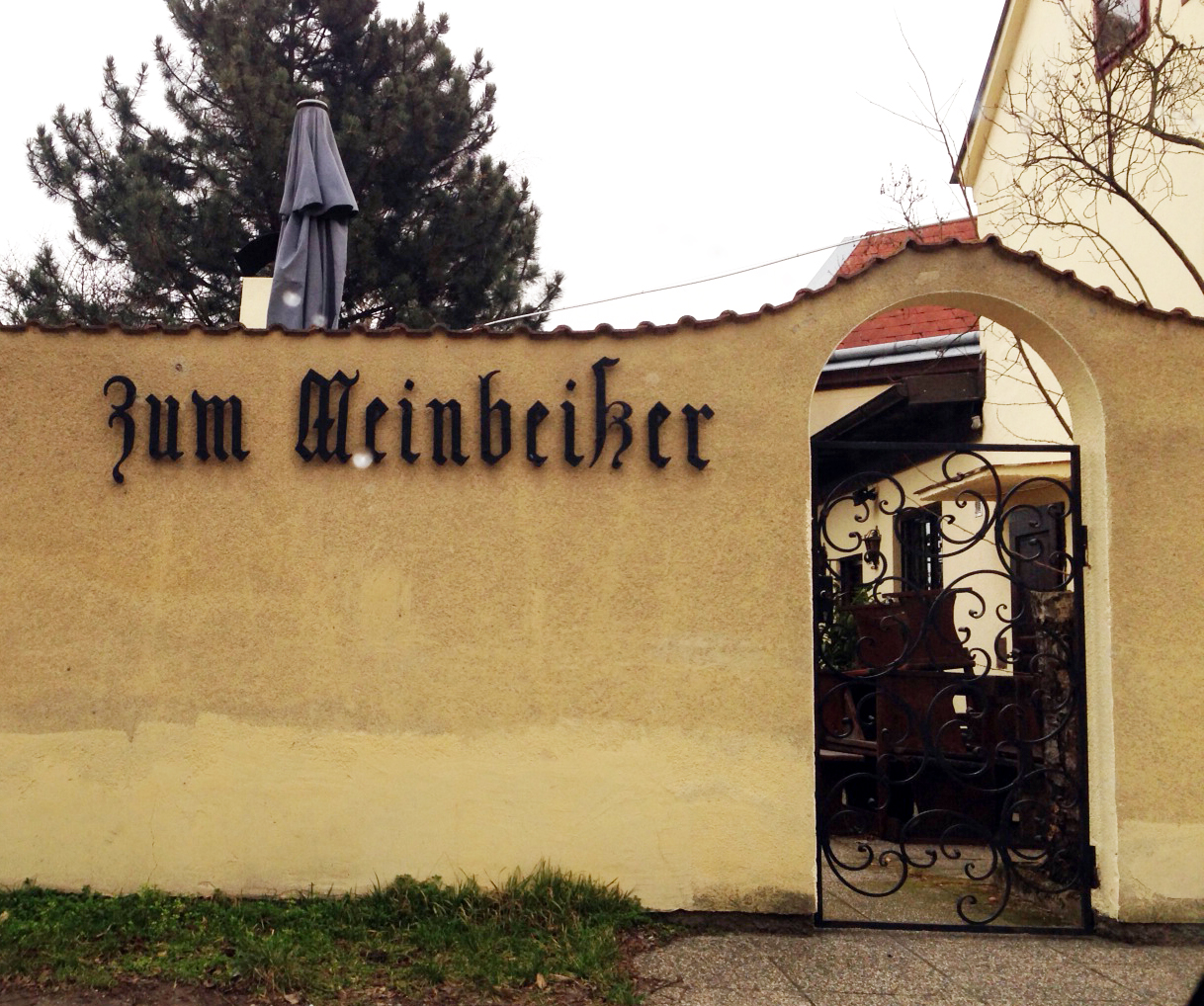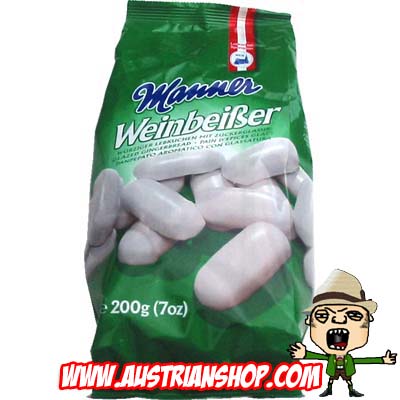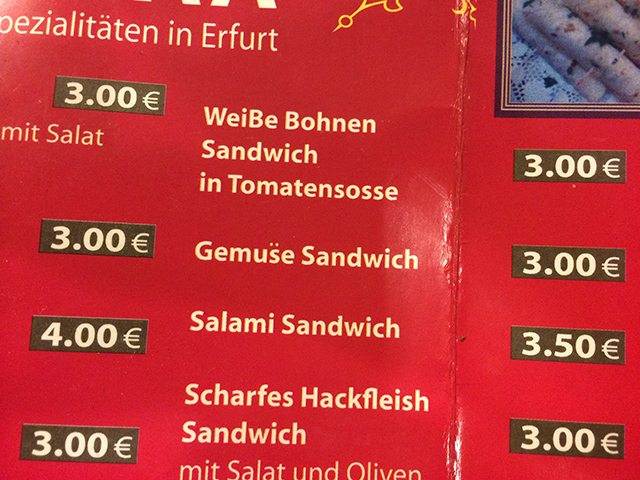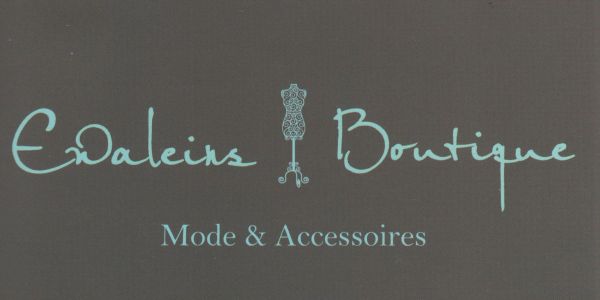
So sind sie nun mal, die Leute, die vorgeben deutsch zu sprechen, und dann Obers, Topfen, Ribiseln, Marillen und eben Weinbeißer haben
Und da ist der Weinbeißer eben dreierlei:
1. Ein mit weißem Zucherguss überberzogener Lebkuchen in Form einer Biskotte (noch so'n Ösi-Wort für Löffelbisquit)
2. Ein anspruchsvoller, den Wein bewusst genießender Weintrinker und -kenner (der den Wein eben noch ein paar mal durch den Mund z
3. Eine  dünne rohe Wurst (die man zum Wein isst)
Oder meinst du, weil sie's mit ss schreiben? Nun, die wollen das wohl auch den Schweizern schmackhaft machen.
Aber wie spicht sich der Firmenname eigentlich in Russland?
Manner macht's auch nicht wirklich besser ...
Die können schon, wenn sie denn wollen …
Kleiner nachtrag zum weinbeißer:
der nette heurigenwirt hat auch noch einen seiteneingang! der wahnsinn hat methode!
Dies erinnert mich an eine Begebenheit in den 1980er Jahren in Hamburg Barmbek:
Dort gab es einen Supermarkt, der auf einem Grundstück zwichen mehrstöckigen Wohnhäusern lag. Der Parkplatz war also durch die glatten Brandmauern der Häuser begrenzt, und darauf wurden dann Ülakate mit den Sonderangeboten der Woche angebracht. Damals wurden für diesen Zweck noch weiße Papierbahnen angeklebt, die dann noch mit einem Pinsel von Hand beschrieben wurden, mal mehr, mal weniger leserlich unmd das Beschriften war dann nicht selten ein Job für Auszubildende.
Ich stand also auf diesem Parkplatz, um in diesem Markt einzukaufen und beobachtete den pinselnden jungen Mann, der da gerate schrieb:
Jachtwurst 100g -,99 (Preis weiß ich nicht mehr so genau)
So rief ich zu ihm rauf: „Yacht schreibt man aber mit Ypsilon!“ (In Hamburg spricht man Jagtwurst ja auch so aus, ixch dachte, der Chef hat dem Juungen Mitarbeiter die Sonderangebote diktiert)
“Wie jetzt, ehrlich?“ „Ja, Yacht schreibt man mir Y!“  „Und was mach ich jetzt, ich kann dfas alles ja nicht noch mal an malen“ „Nun, aus J lässt sich doch wohl, ohne dass dies auffällt, ein Y pinseln“ „Jo, aber da frag ich wohl besser noch mal den Chef?“ „Ja, mach das mal, besser is‘. Sollst ja keinen Ärger bekommenn“
Der Pinseler kletterte von seiner Leiter, legte den Pinsel bei Seite und machte sich auf den Weg ins Supermarkt-Büro, ich schnappte mir einen Einkaufswagen und ging in den Markt, un sort den Wochen-Einkauf zu erledigen.
Als ich dann mit gefülltem Einkauswagen den Markt wieder verlassen hatte, wurde da tatsächlich für die nächste Woche die echt maritime Yachtwurst angeboten. Ob die Kunden sich wohl gewundert haben, wenn sie an der Wursttheke diese neue Spezialtät im Hafenbstadt-Stil bestellt, und dann doch nur hundsordinäre Jagtwurst bekommen haben?
wurde da tatsächlich für die nächste Woche die echt maritime Yachtwurst angeboten.
Und das hast du nicht fotografiert‽ :hammer:
Ne, jeider war das noch zu einer Zeit, in der man seinen Foto-Apperat nur dann dabei hatte, wenn man bewusst fotografieren wolltew, also z.B. im Urlaub,. und nicht zu Einkaufstouren. Handys mit Foto-Funktion gabs noch nicht, War jemand tatsächlich mit einem mobilen Telefon unterwegs hatte man damals Kiloschwerde C-Netz Kisten, die manche wie Umhängetaschen herumschleppten.
Aber ehrlich, ich habe mich schon oft geärgert, dass ich und meine Eltern kaum das alltägliche Stadtbild, sondern fast immer nur Familenmitglieder als Fotomotiv angesehen haben Nicht selten sind Fotos, die fremde einfach so vom Straßenbilds von Damals gemacht haben, mit mehr Erinnerungen verbunden, als die üblichen Familienbilder. Aber selbst da: Wer fotografierte schon die Preisaushänge von Supermärkten?
Schon klar, das mit den anderen Zeiten. Aber in solch einem Fall wäre ich vielleicht doch schnell nach Hause gelaufen und hätte meine Penti geholt.
Wenn das mit „nach Hause laufen“ in diesem Fall möglich gewesen wäre, ja, aber ich wohnte damals in Altoma Nord, und wear nur wegen einem Besuch in einem Elektronik-Markt in Barmbek.
Ähm … Ewaleins? Das »Boutique« sieht ja hübsch aus (mal abgesehen vom Übergang ou), aber das andere Wort ist eine ungünstige Aneinanderreihung von auf den ersten Blick nicht zweifelsfrei erkennbaren Buchstaben.
Laserdrucker, Tintenstrahler und Offsetmaschinen sehen plötzlich tanzschön alt dagegen aus ;-)
Hier noch eins:
Da müssen wir aber einen ganzen Satz hinkriegen – wegen der Leerzeichen sonst kommt Kathrin nicht ...  :tuschel: